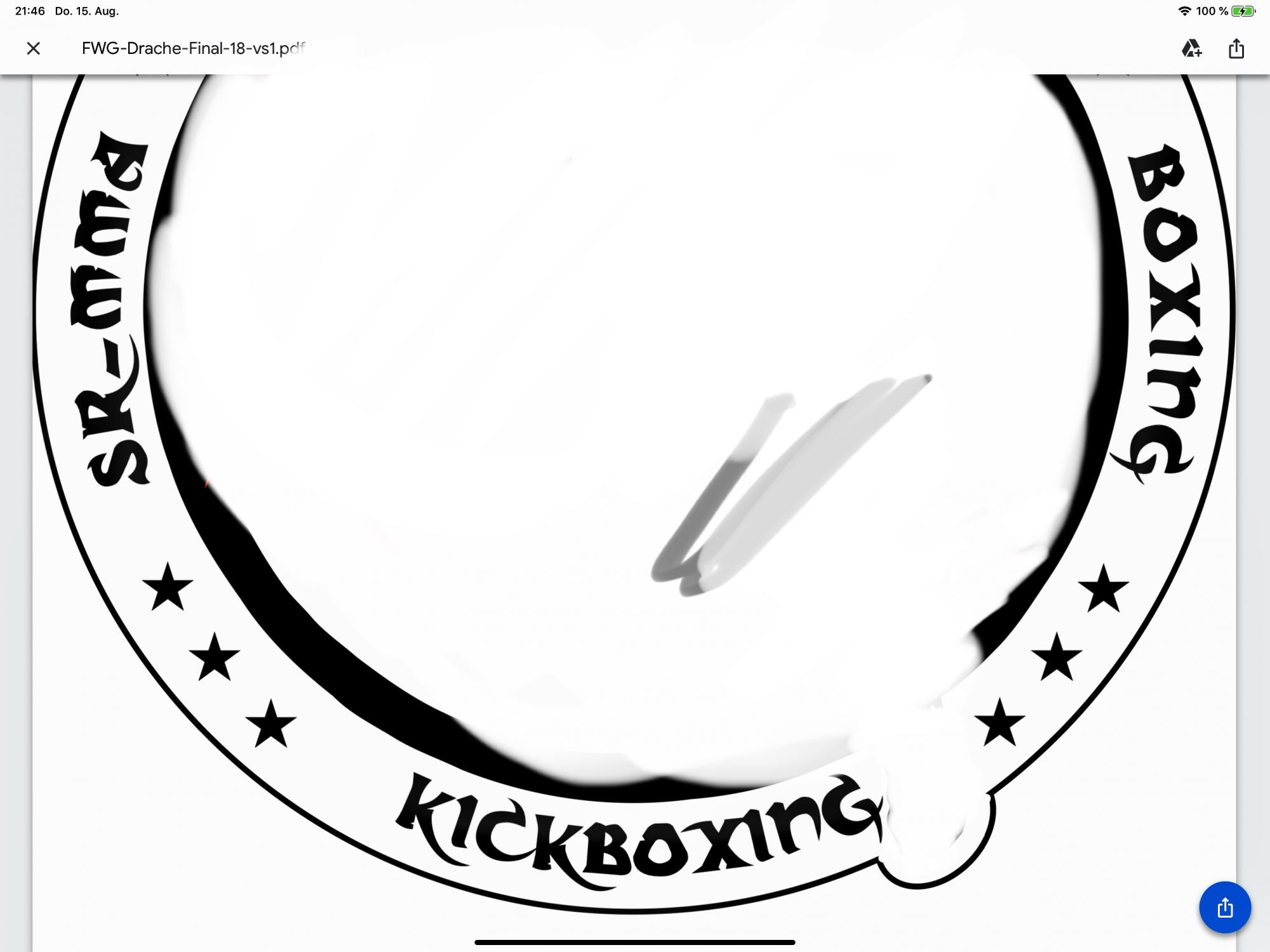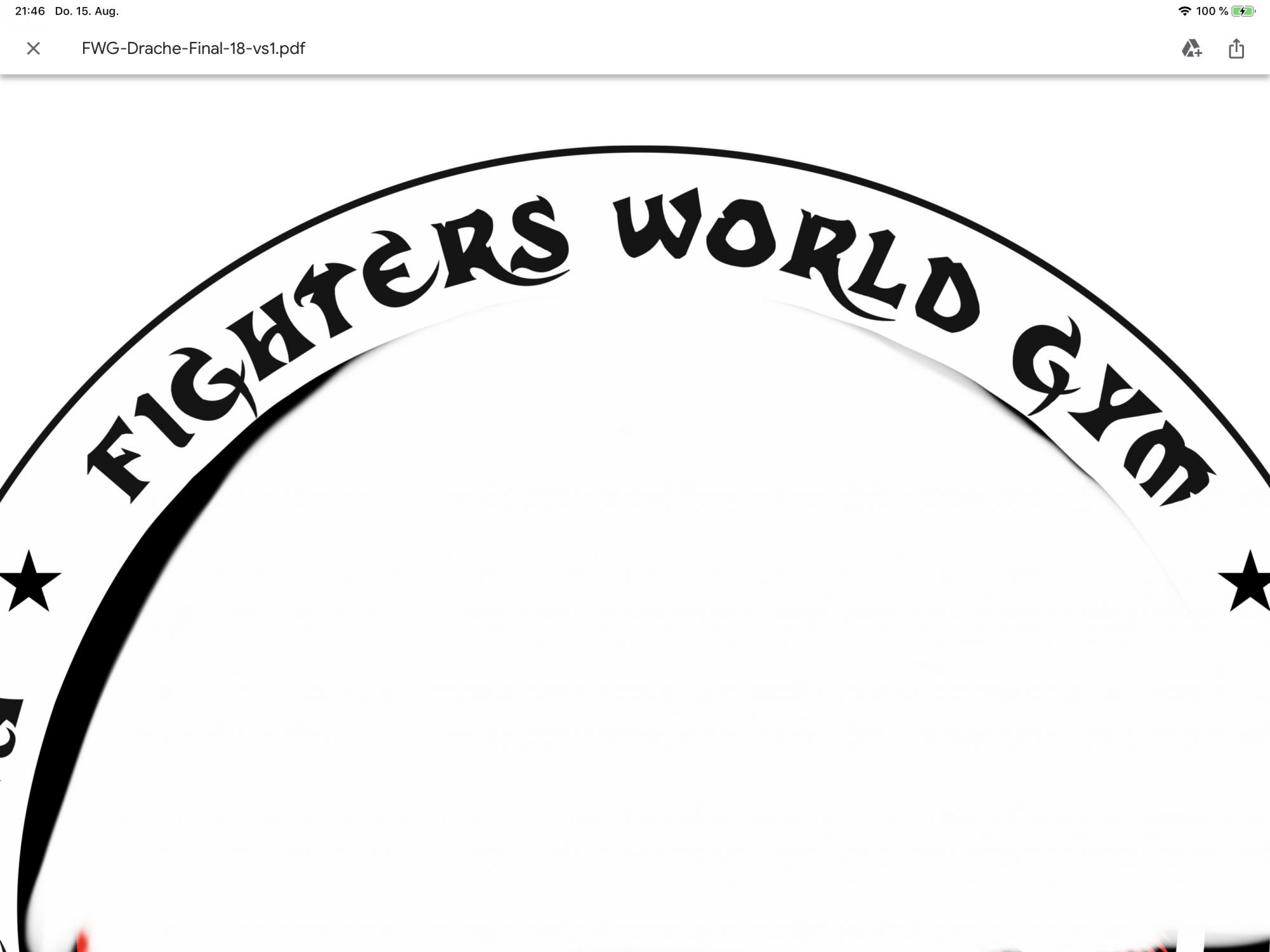
Suche Schriftart von unseren Vereinslogo (Fighters World Gym)
ich hoffe auf diesem Wege herauszubekommen, um welche Schriftart es sich in unserem Vereinslogo handelt.
Leider ist der Erschaffer des Vereinslogos verstorben, so dass man ihn hätte befragen können.
Für mich schaut die Suche nach einer gewaltigen Fleißarbeit aus. Das gesendete Bild schaut nicht so aus, als läge es in der vom Gestalter erzeugten PDF-Datei vor, oder sonst einem Grafikformat mit noch eingebundenen Schriftzeichen.
Dann können Schrift-Erkewnnungsprogramme nicht viel mit Schriftzeichen, die im Kreis gesetzt sind, und sich auch noch überlappen (wie beim K) anfangen, man müsste also erst einmal einige typische Buchstaben ausschneiden, und genau senkrecht stellen und so anordnen, dass es senkrecht zwischen den Buchstaben eine klare Grenze gibt. Trotzden ist hier die Erkennungsrate bei derartiger Schrift eher niedrig, und ich denke mal, das wird auch irgend ein freefont sein.
Also bliebe wohl nur, z.B. das Angebot von dafont.com zu durchsuchen. Da gibt es wirklich Tonnen von Fonts, jedoch hat sich der Betreiber viel Mühe gemacht, die dort hochgeladenen Schriftarten nach Themen zu sortieren, das bedeutet, bei solch deko-Schriften braucht man sich wenigstens nicht durch klassische S chriftformen hindurch zu wühlen. Allerdings komme ich auch nicht so recht auf die Idee, in welchem Thema ich die Schrift einsortieren würde, Und gerade bei entfernt ähnlichem gibt es gerade hunderte Seiten zu je 50 Schriftarten
vor einer Stunde schrieb catfonts:
Allerdings komme ich auch nicht so recht auf die Idee, in welchem Thema ich die Schrift einsortieren würde
Ich würd‘s bei Pseudo-Asiatisch versuchen :-?
https://www.dafont.com/de/theme.php?cat=201
… oder »damaged« oder ähnlichen in der Schriftverschlagwortung üblichen Termini.
Passt aber irgendwie zum Kampfsport. Them fighters get banged up pretty good … :shock:
Es ist die Schriftart Dark Crystal aus dem Gothic und zwar die kleinen Buchstaben.